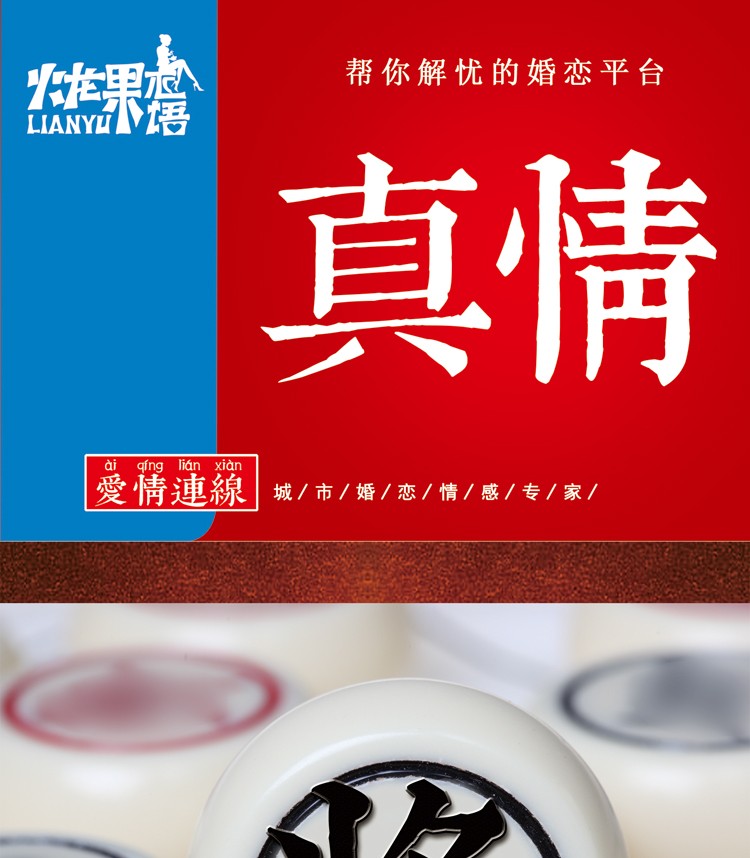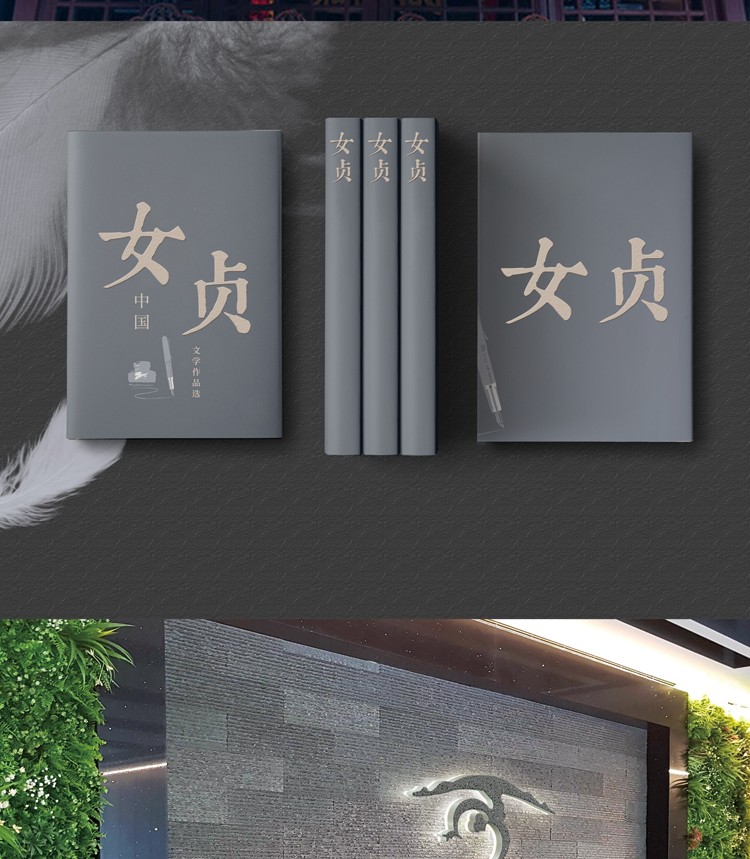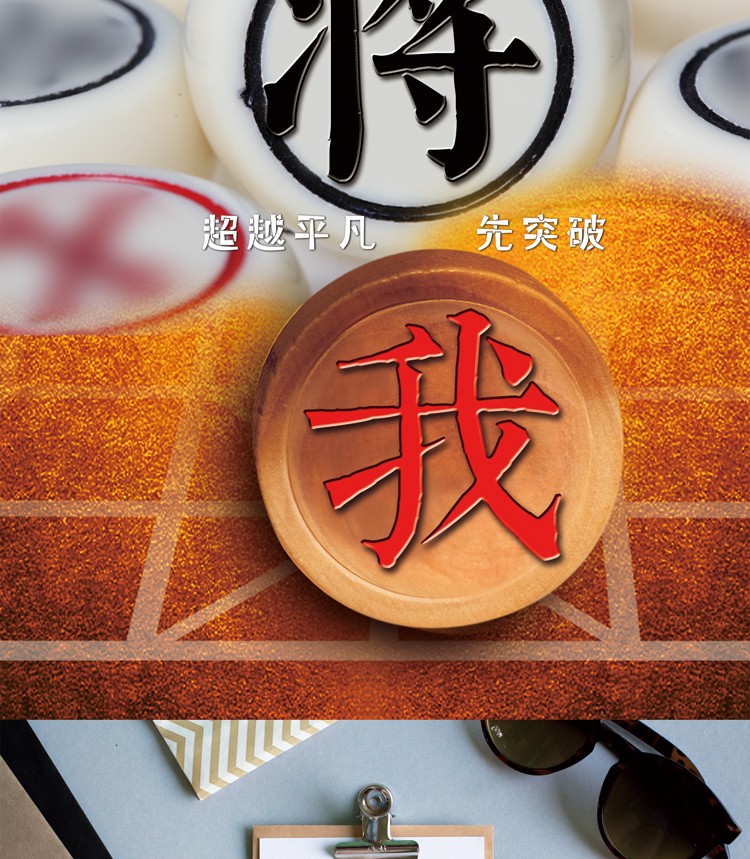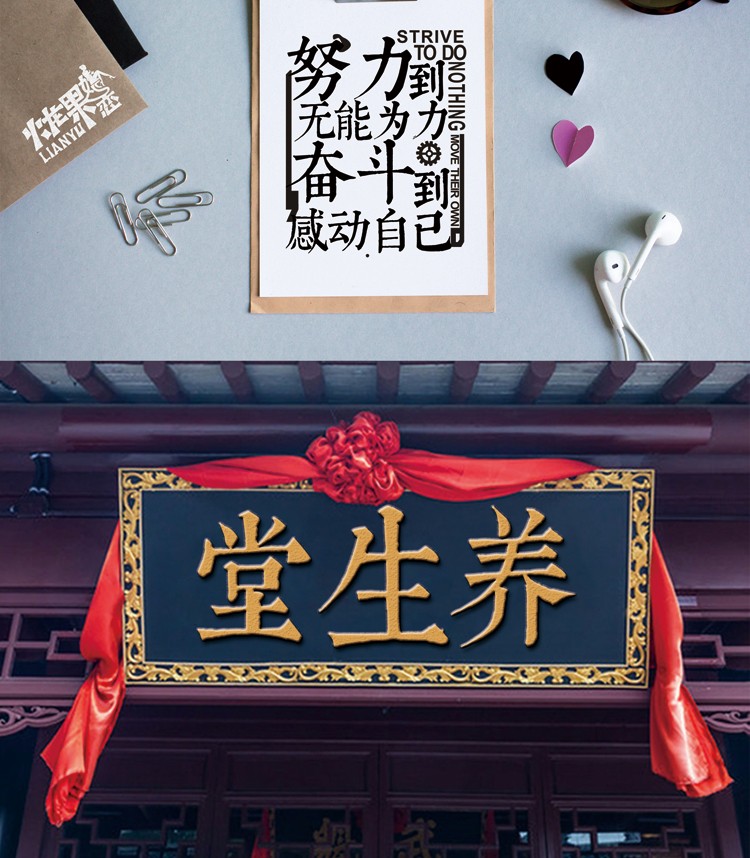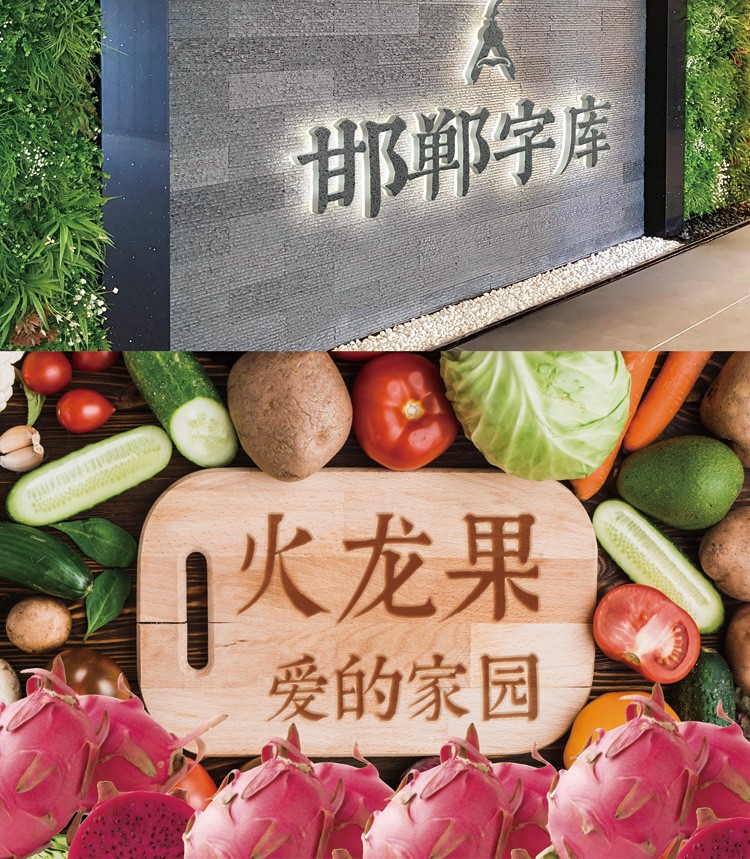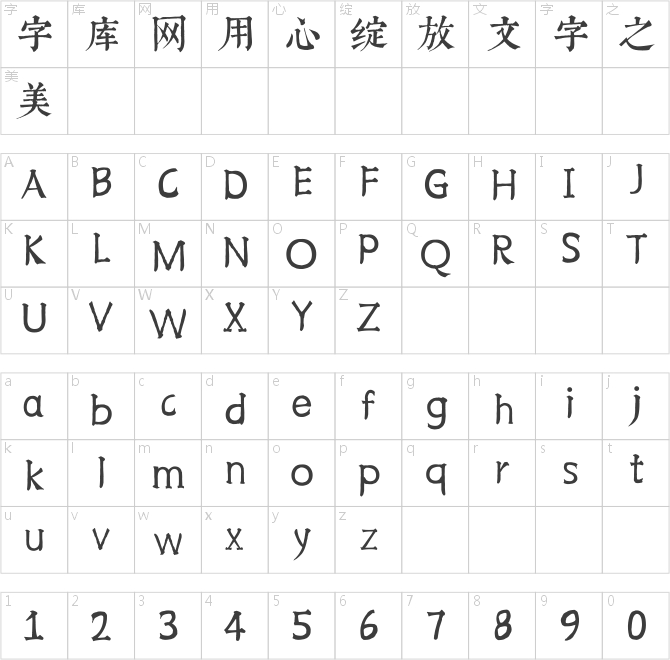
字体名称: 邯郸康熙字典体
作者版权: 韩绍杰
邯郸康熙字典体介绍
大字库繁简精全共47549字
邯郸康熙字典体字体邯郸康熙字典体【繁简精全47549字】字库是一款让人赏心悦目、百看不厌的中文字体,适合各类广告和产品包装设计应用,字体大小51.56MB,格式为ttf字体,上传用户是邯郸字库,作者/版权方为韩绍杰